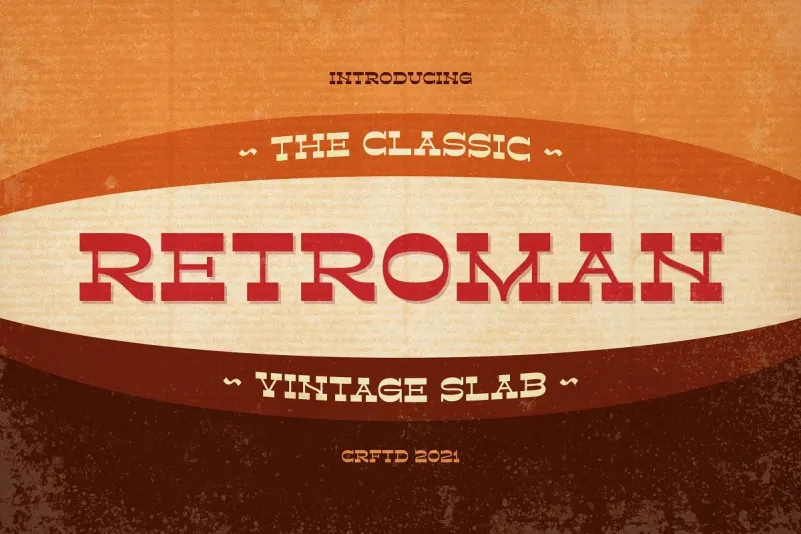
Retroman Font
Retroman Font é uma slab serif que retrata claramente a influência dos fonts clássicos com um toque retro, misturando nuances de estilo de tipo Slab que remetem ao início do século 80. Inspirada nos anos 70 e 80, esta fonte mantém o carácter moderno e compacto de seu antecessor, enquanto incorpora elementos decorativos típicos da era dos anos 70 e 80. Sua tipografia retrógrafa oferece uma aparição que é tanto atual quanto clássica, tornando-se perfeita para um design criativo que se encaixa perfeitamente em qualquer tipo de projeto gráfico. Ideal para aplicar em elementos visuais modernos e contemporâneos com estilo antigo, Retroman Font está disponível no catálogo de 99designs como uma opção elegante para designers de todo o mundo.